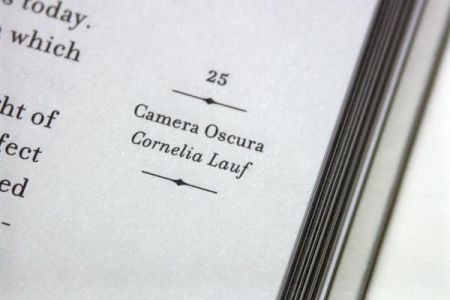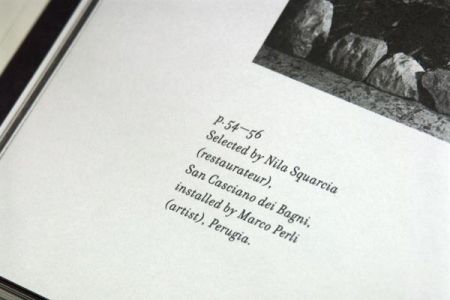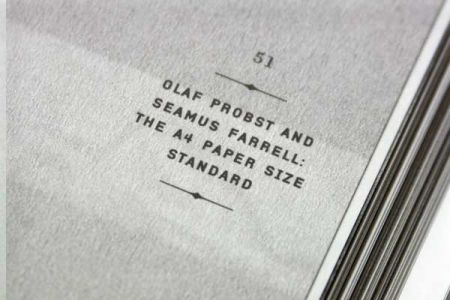
camera oscura / cornelia lauf
suche zwei schriften, die im katalog von cornelia lauf mit dem titel camera oscura verwendet wurden (siehe beispiele). gefallen mir beide außerordentlich gut, habe aber leider nur diese beispiele, die bei whatthefont keine ergebnisse liefern.
kann jemand helfen?
danke! und das zu der uhrzeit!! jetzt nur noch die serifenlose und das wochenende kann kommen...
dachte am anfang, dass die evtl. von lineto sein könnte, habe aber nach recherche leider nichts gefunden.
jetzt nur noch die serifenlose und das wochenende kann kommen...
Zur Grotesk: kann ich leider nicht helfen, die 4 ist aber sehr markant.